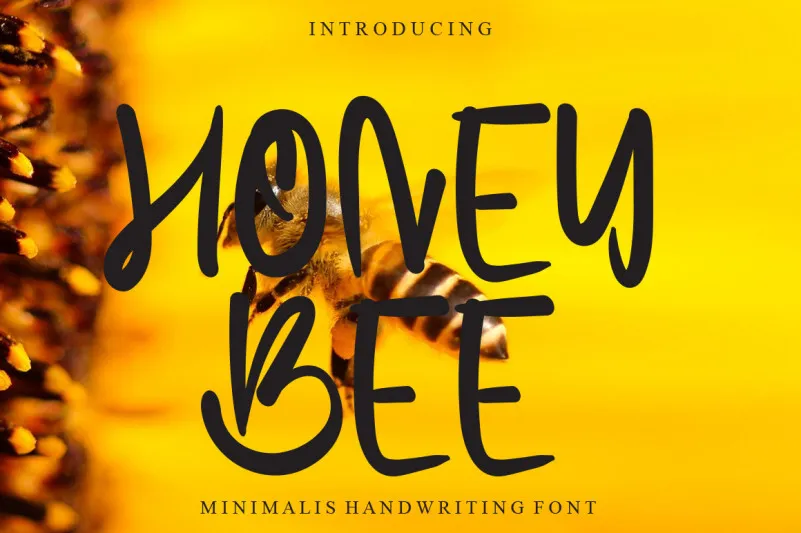
Honey Bee Font – Download Grátis
Esta é uma fonte escrita a mão, delicada e cíntica. Ideal para aqueles que buscam algo único e autêntico para dar um toque especial a seus projetos de design. Seu aspecto suave será uma grata surpresa em qualquer projeto. A Honey Bee Font traz uma atmosfera encantadora e romântica, tornando cada obra sua uma experiência agradável de olhos. Suas linhas fluidas e elegantes criam um visual que é tanto perfeito para projetos visuais quanto para texturas gráficas. Seja você um designer de logotipos ou um ilustrador, essa fonte é certamente o elemento complementar perfeito para dar um toque diferenciado aos seus trabalhos. Ideal para aplicação em logotipos, cartões de felicitações, editoriais e outros tipos de design gráfico que buscam ser delicados e românticos ao mesmo tempo. A Honey Bee Font é uma escolha certa se deseja trazer um toque único a cada projeto que criará.